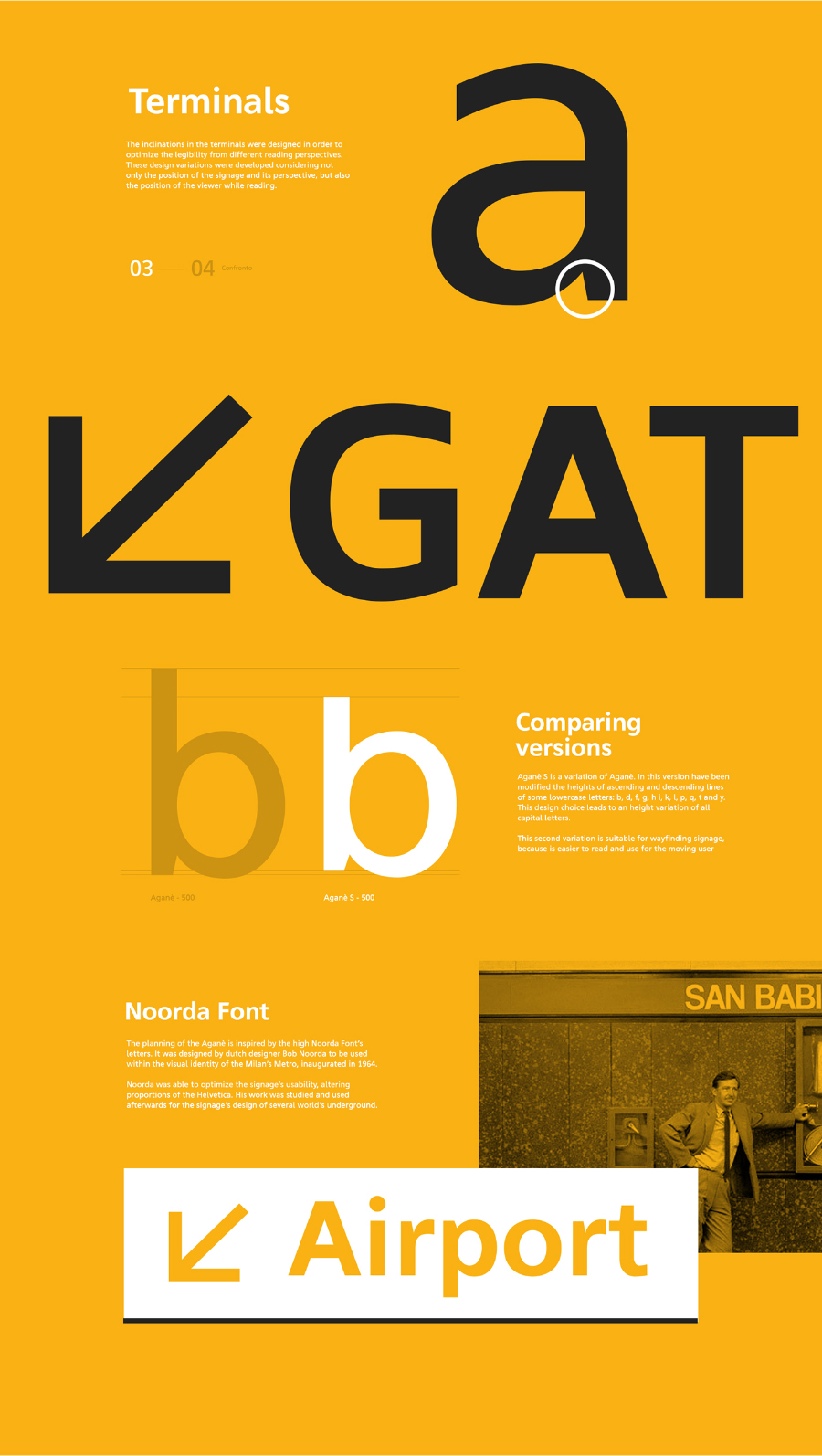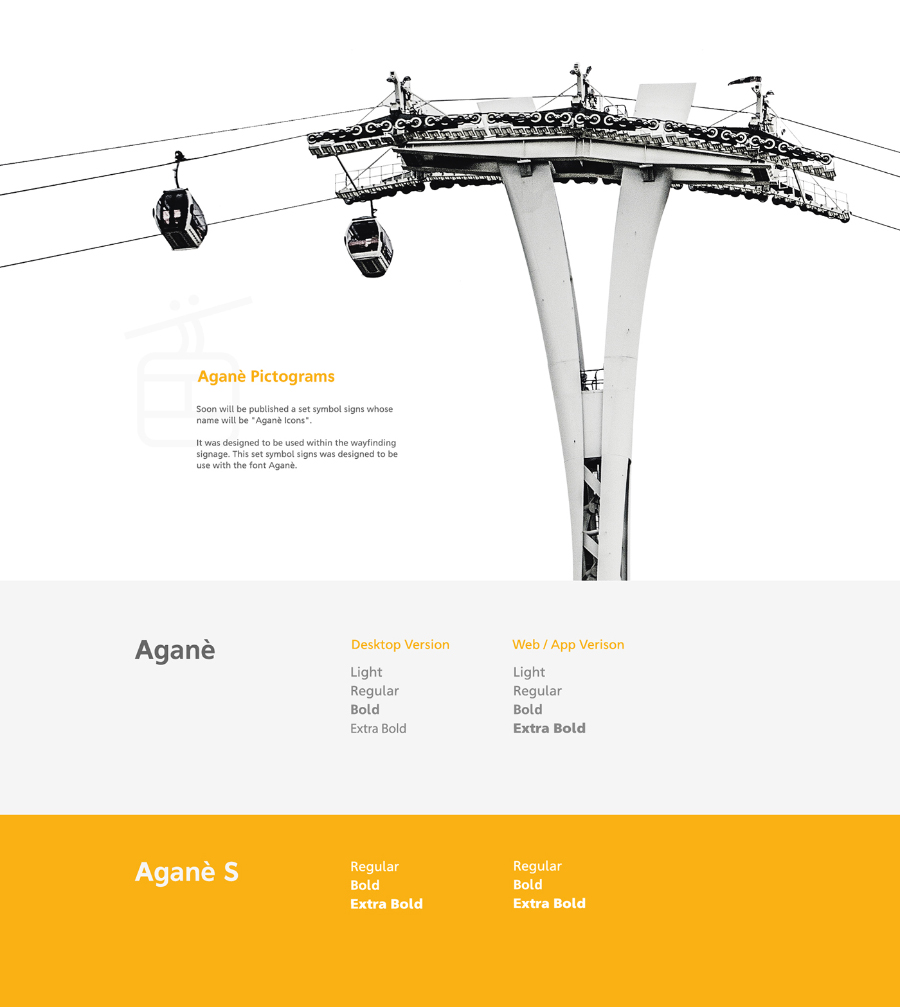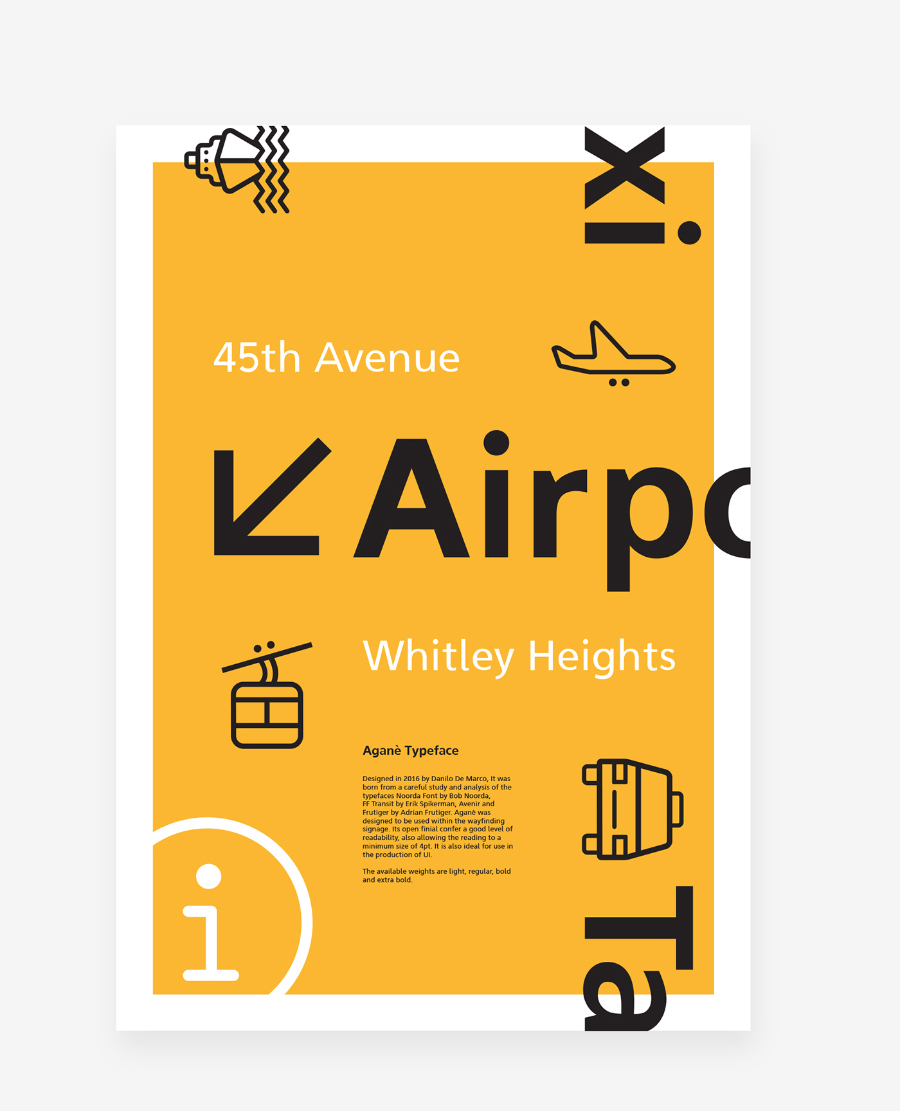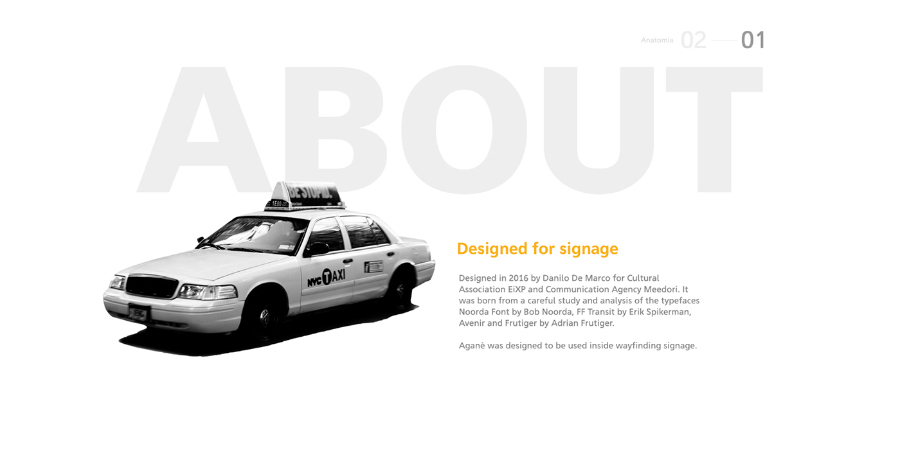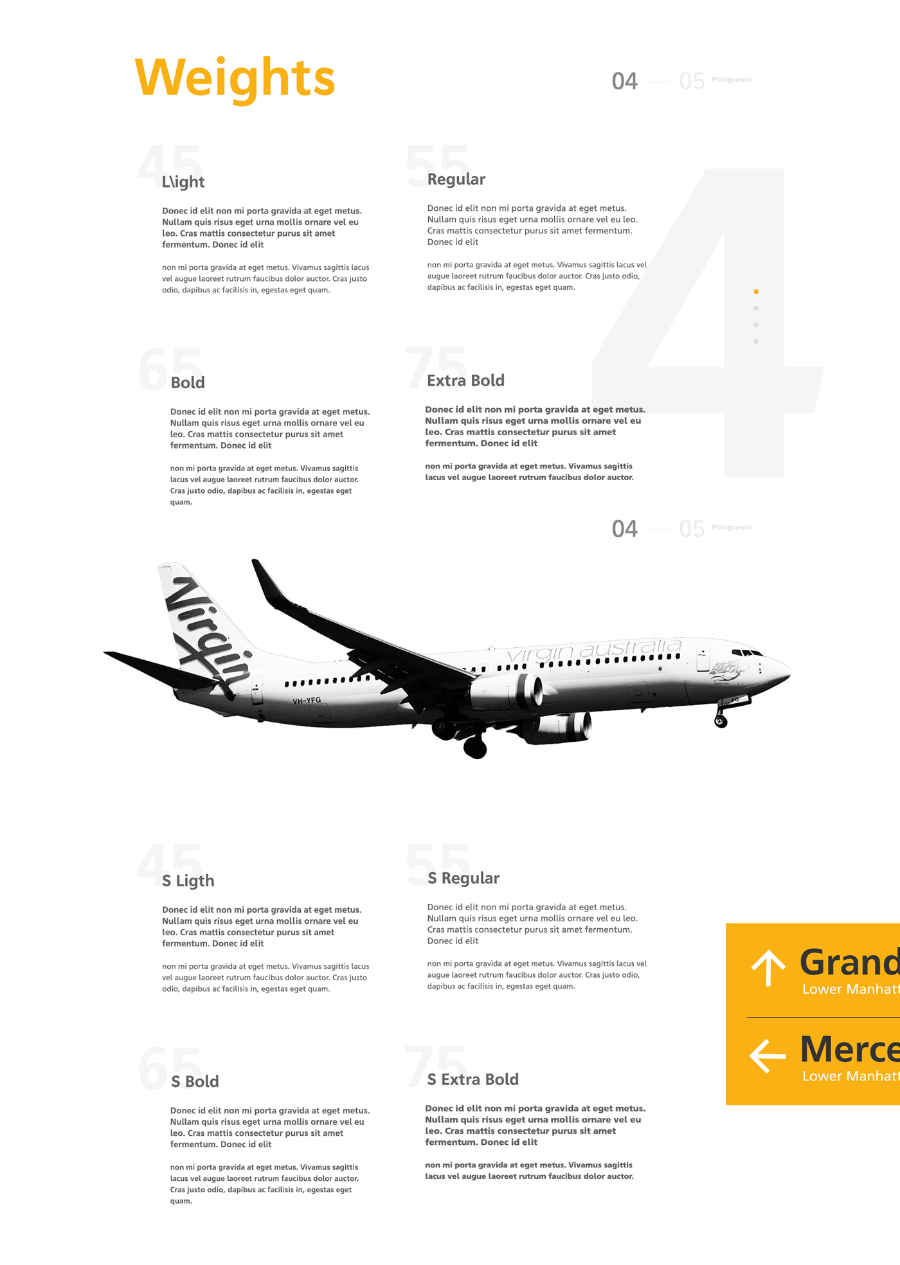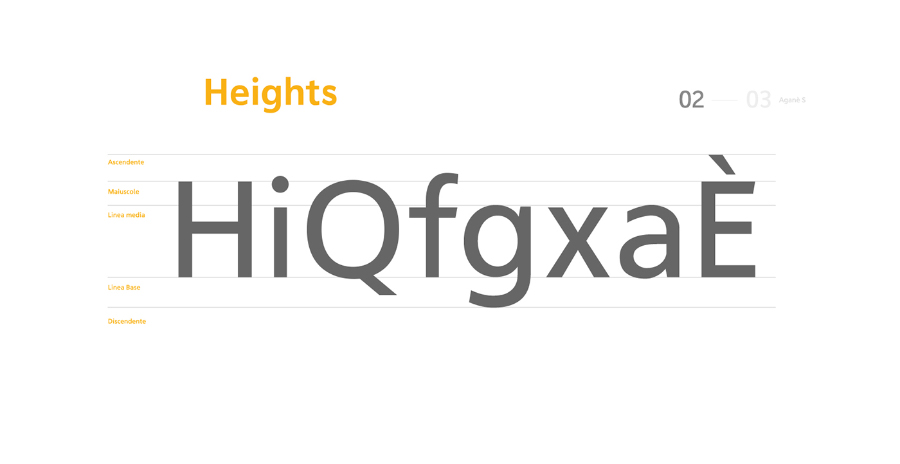
Aganè免费免费字体
Agane Sans Free字体设计于2016年,由Danilo De Marco设计。它来自于Bob Noorda,Avenir和Frutiger的字体Noorda Font by Adrian Frutiger的仔细研究和分析。 Aganè被设计用于在指路标志中使用。它的开放性有助于提高可读性,并使读数最小为4pt。它也是用于制作UI的理想选择。可用的重量轻,规则,粗体和特大胆